Während im Westen Buchstaben Laute abbilden, stehen die ostasiatischen Zeichen für ganze Begriffe und Bedeutungen. Über Jahrhunderte wanderten sie mit Mönchen, Beamten und Händlern entlang der Seidenstraße — und wurden in jeder Sprache neu ausgesprochen, ohne ihre Form zu verlieren. Japanische Kana, koreanisches Hangul und das vietnamesische Chữ Nôm sind Antworten auf dieselbe Frage: Wie viel von der eigenen Sprache passt in chinesische Zeichen?
Ostasien
Von der Kaiserlichen Kanzlei bis zum Reisbauern am Yangtse: Ostasien hat über drei Jahrtausende eine eigene Schriftwelt geprägt. Aus Orakelknochen wurden Pinselzeichen, aus Pinselzeichen ein gemeinsames Erbe für China, Japan, Korea und Vietnam.
Eine Region, viele Schriften
Zeichen zwischen Kontinent und Insel
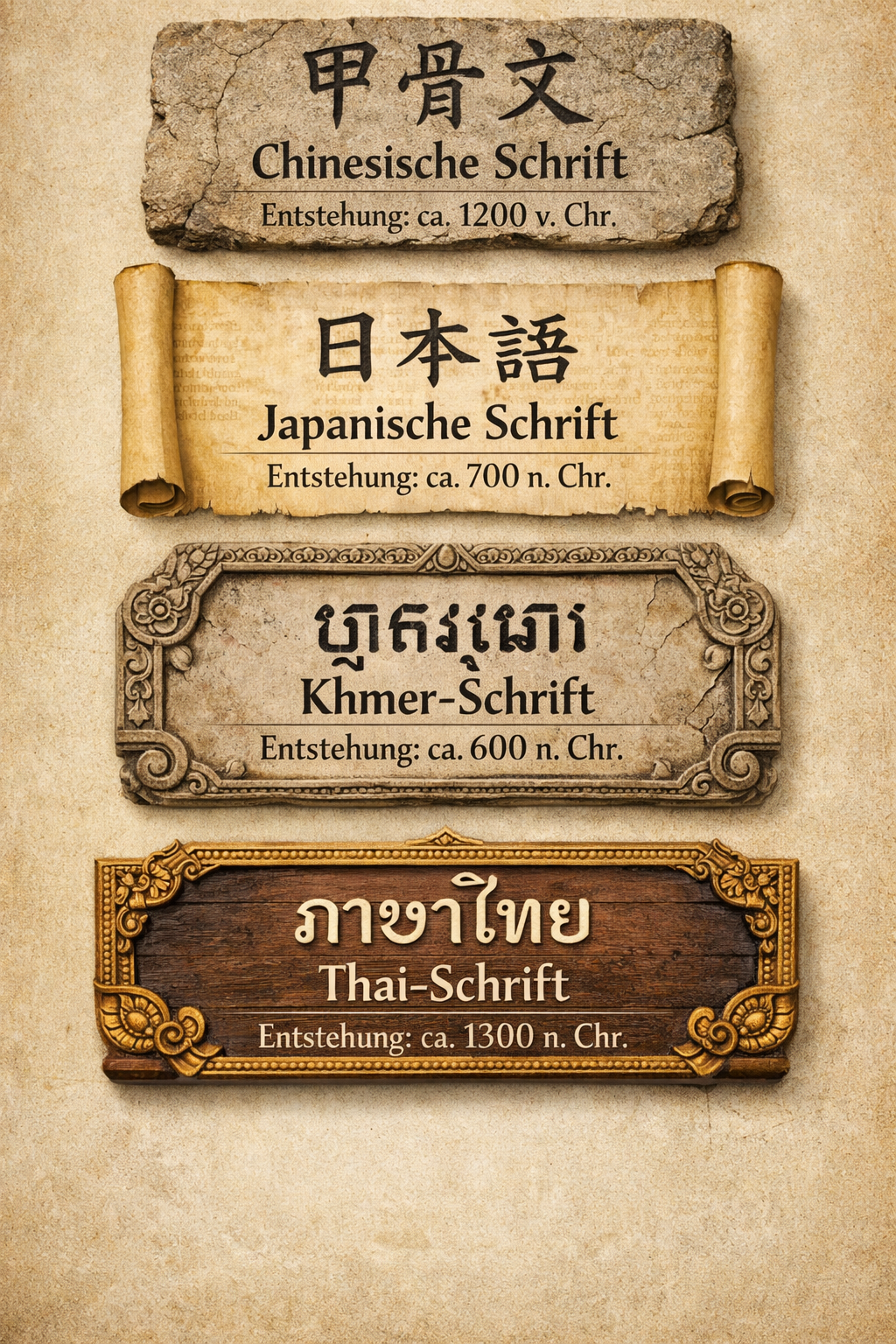
China bis Japan
Pinsel, Papier und Tradition
Die Karte zeigt die Reichweite chinesischer Schrift und ihrer Nachbarn. Tusche auf Reispapier, Pinsel im Bambusrohr — die Werkzeuge haben sich kaum verändert. Aus dem Zeichen für „Berg“ wurde nie nur ein Symbol; es blieb auch Bild.